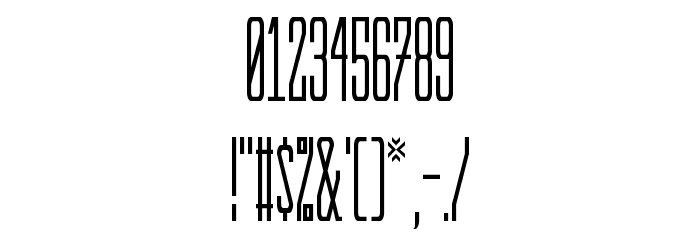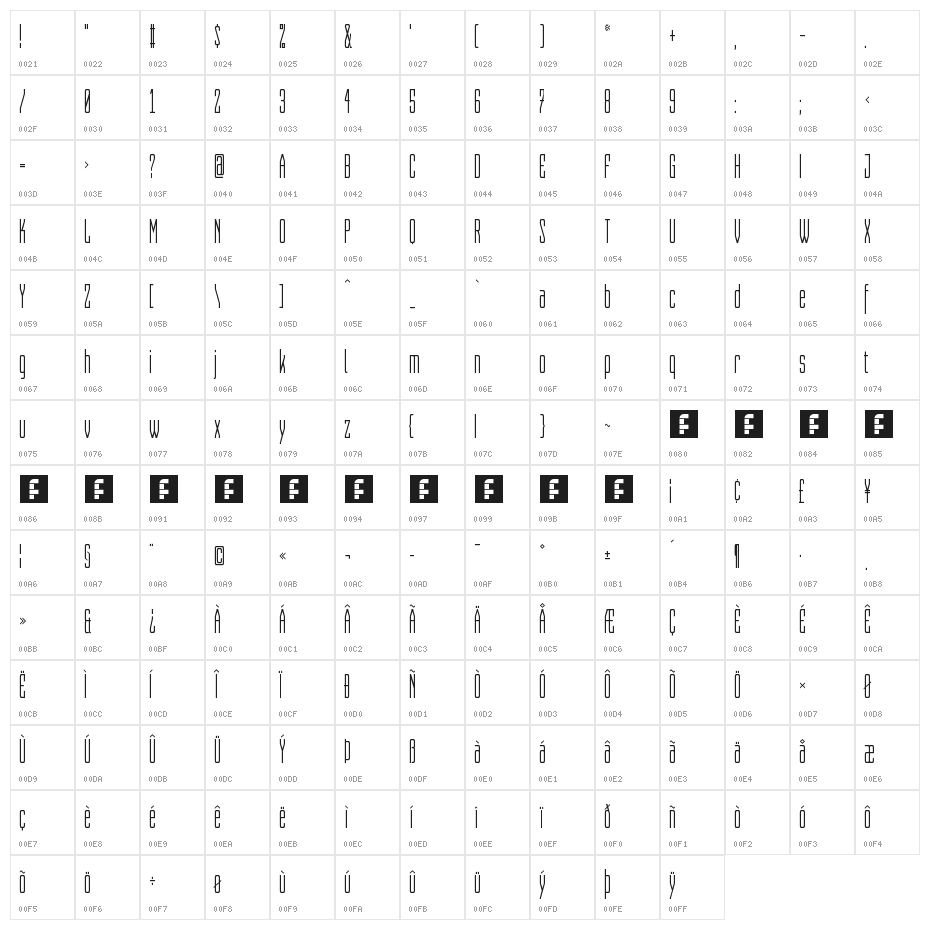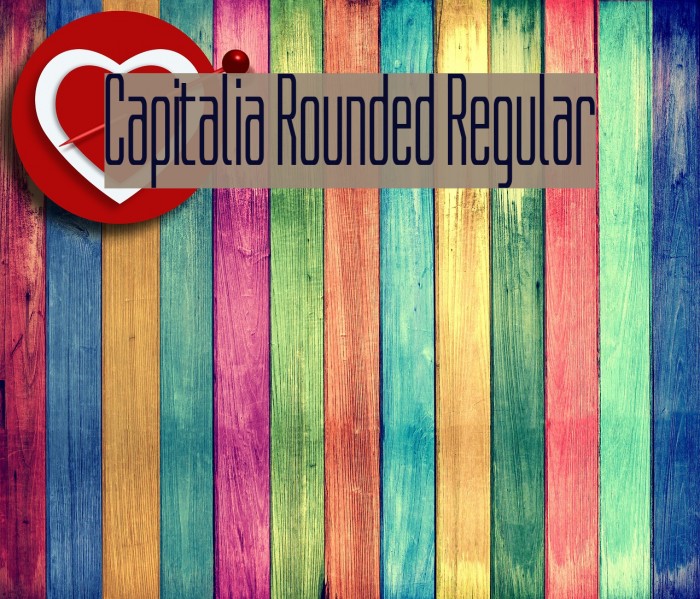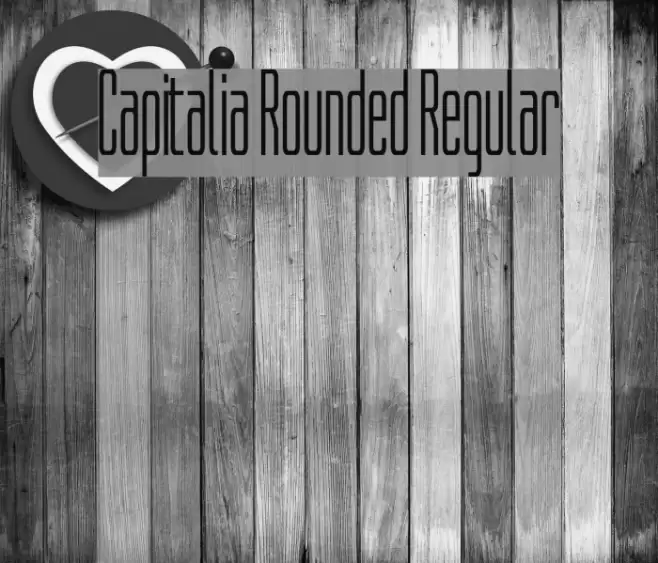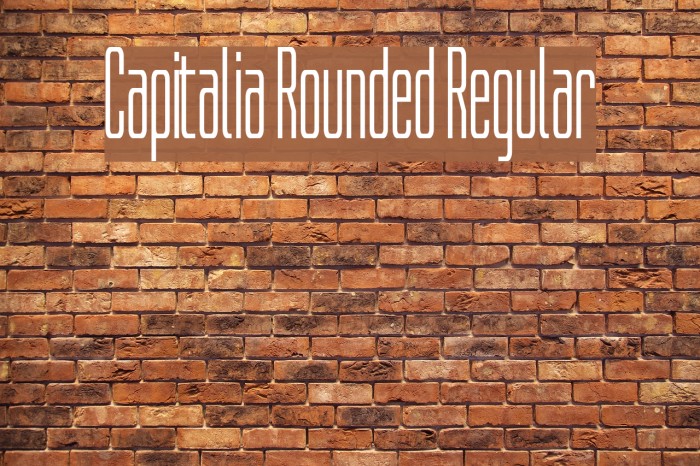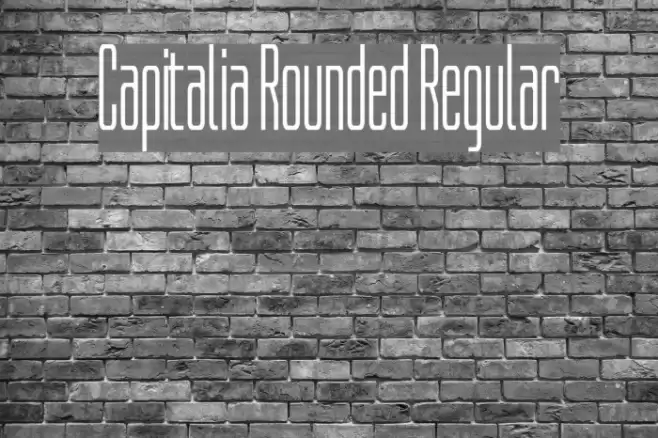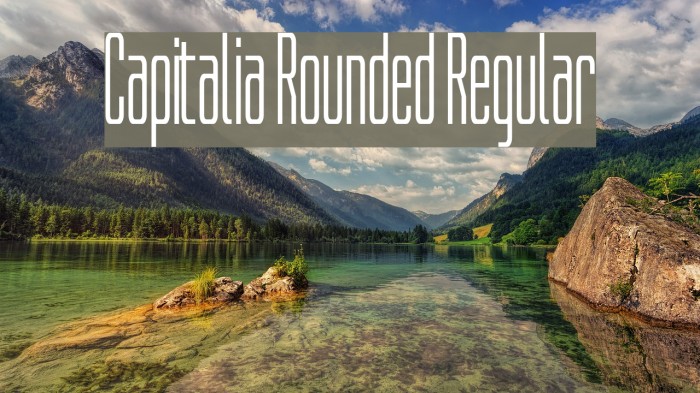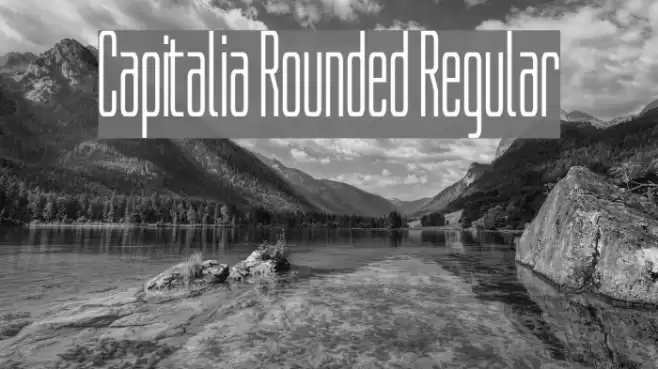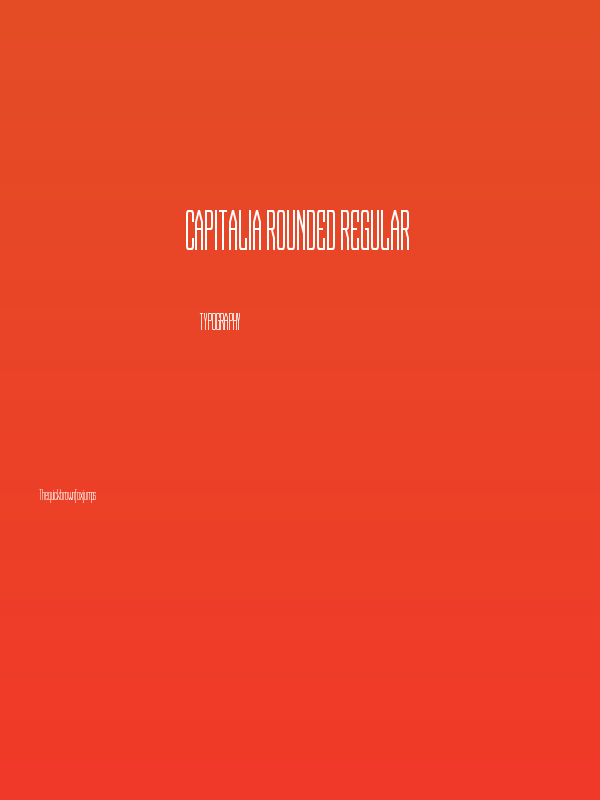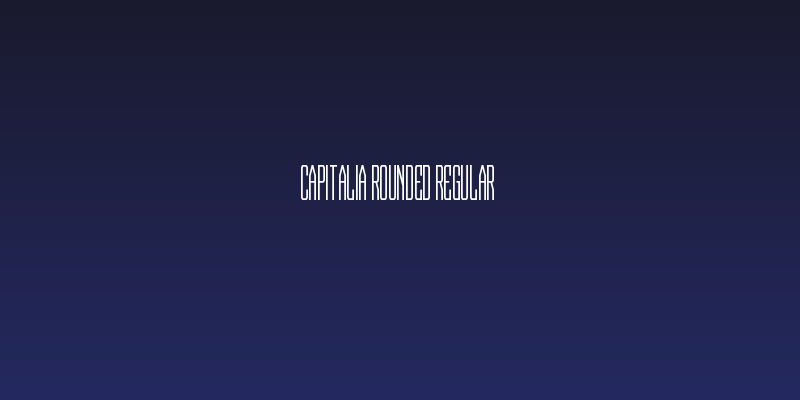
Capitalia Rounded Regular Font
| Caso d'uso | Headlines, Logos, Branding |
| Progetti proposti | Ideal for branding, packaging, and editorial design where a modern and approachable aesthetic is desired. |